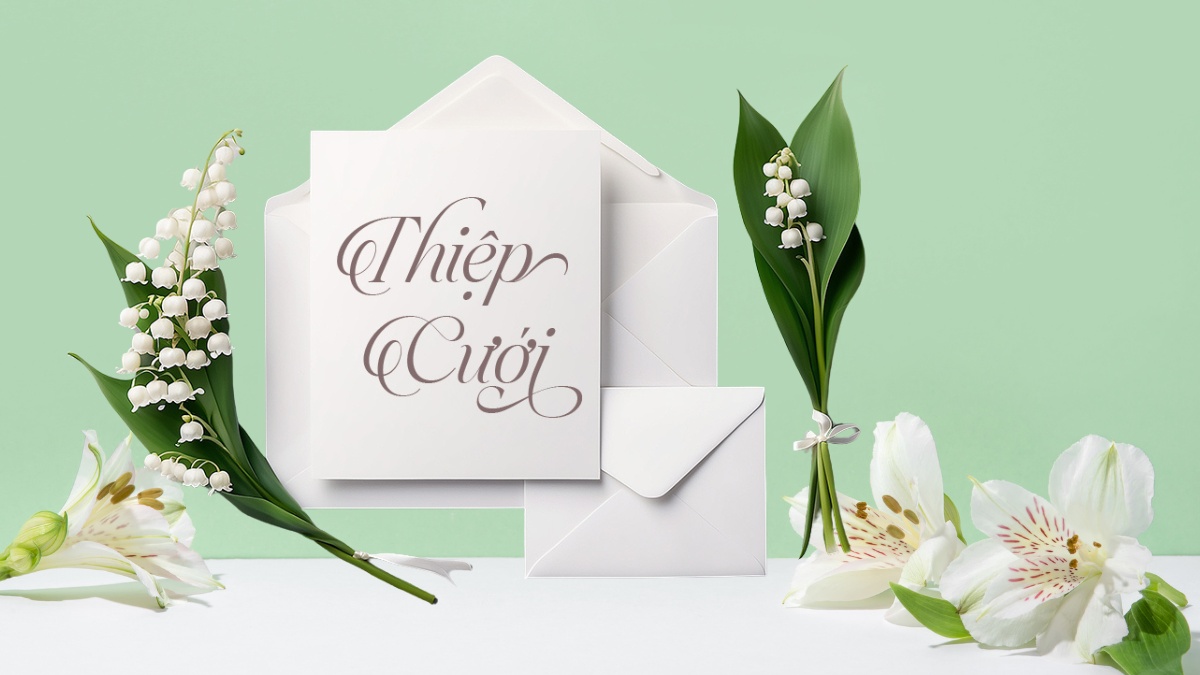
15 Font chữ viết tay tiếng Việt đơn giản, siêu đẹp
Font chữ viết tay tiếng Việt đẹp, đơn giản được ứng dụng rất nhiều trong các sản phẩm in ấn, poster, thiệp mừng... Đây là lựa chọn của nhiều người khi muốn mang đến một thiết kế cổ điển, gần gũi và hiện đại. Nếu bạn muốn tìm hiểu về những font chữ viết tay vintage hay hiện đại, thời thường thì hãy đọc bài viết này. Sforum chia sẻ đến bạn 15 mẫu font chữ đa dụng và phổ biến nhất.
Font VN Griffiths
VN Griffiths là một font chữ viết tay tiếng Việt vô cùng thông dụng và được xuất hiện ở rất nhiều nơi. Đây là sự lựa chọn hoàn hảo để bạn cho ra đời những thiết kế thiệp cưới đầy tinh tế và sang trọng. Với đường nét trang nhã, mẫu chữ này được nhiều người nhận xét rất dễ đọc, không gây rối mắt cũng như tạo cảm giác thanh thoát, nhẹ nhàng. Ưu điểm của font chữ VN Griffiths phải kế đến sự thanh lịch, mềm mại, hơi hướng cổ điển nhưng vẫn rất gần gũi và hài hòa.
VN Lovelista tiếng Việt
VN Lovelista rất được yêu thích bởi font chữ đẹp, đơn giản phù hợp với nhiều dự án thiết kế. Người dùng có thể ứng dụng trong các bài đăng mạng xã hội, trích dẫn, thiết kế logo, bảng hiệu, áp phích, biểu ngữ website,... Điểm nhận dạng của font chữ này phải kể đến những nét thanh đậm rõ ràng mang hơi hướng nhẹ nhàng, bay bổng. Đây chắc chắn là một font chữ hoàn hảo cho các thiết kế đơn giản nhưng vẫn làm nổi bật các thông điệp cần truyền tải.
Font VNI Zap
Nhắc đến những font chữ viết tay đơn giản và mang phong cách hiện đại, gần gũi với người Việt không thể thiếu font VNI Zap. Font chữ này rất phổ biến trong nhiều thiết kế. Đây cũng là lựa chọn hàng đầu của cộng đồng thiết kế đồ họa. Nếu bạn muốn sản phẩm của mình có tính sáng tạo và đột phá thì đừng bỏ qua font VNI Zap. Với sự đa dạng và linh hoạt trong kiểu chữ, các nhà thiết kế sẽ có thêm nhiều cách để truyền tải thông điệp một cách mạnh mẽ, linh hoạt và thu hút.
Font Việt hóa MTD Yessy
MTD Yessy mang đến một lựa chọn đầy tinh tế và quyến rũ, vừa mang phong cách hiện đại lại vừa cổ điển nên có thể đáp ứng nhiều nhu cầu thiết kế khác nhau. Yessy nổi bật với những đường nét vô cùng nhẹ nhàng, tạo sự dễ chịu cho người xem. Phong cách của font chữ viết tay vintage này rất thích hợp trong các ấn phẩm in ấn và trực tuyến. Đây là lựa chọn lý tưởng để tạo ra những sản phẩm mang hơi hướng sang trọng, thanh lịch.
Font MTD Daytonia
MTD Daytonia là font chữ viết tay tiếng Việt được rất nhiều người dùng, gây ấn tượng bởi những đường nét đầy uyển chuyển và mềm mại. Phông chữ này giúp mang lại sự hài hòa, tự nhiên như thể do con người tự viết bằng tay. Daytonia là lựa chọn hoàn hảo cho việc thiết kế các sản phẩm mang tính cá nhân hóa cao như thiệp mời, bao bì, branding… Nó phản ánh xu hướng hiện đại, sang trọng mang hơi hướng tự do, cá tính.
1FTV Eastin Hikary
1FTV Eastin Hikary là một font chữ đẹp, ấn tượng, mang đến một cảm giác nhẹ nhàng và thanh thoát trong từng tác phẩm. Font chữ này được sử dụng vô cùng hoàn hảo cho những dự án vintage nhưng vẫn đảm bảo thể hiện được nét đẹp hiện đại, sang trọng. Những đường nét mượt mà giúp người đọc rất dễ nhìn và nhận biết. Font chữ này rất được ưa chuộng khi thiết kế bìa sách, tiêu đề, poster, logo,...
VN Cathiy Betiey
- Người sáng tạo: Jamalodin
- Phụ trách tiếng Việt: Huy Nam
VN Cathiy Betiey là font chữ vô cùng độc đáo với nét đặc trưng của những đường nét thanh, đậm rất rõ ràng. Đặc biệt, kiểu chữ in nghiêng mang đến sự uyển chuyển, nhẹ nhàng, lả lướt và tinh tế. Với phong cách độc đáo, ấn tượng, font chữ viết tay đơn giản này có thể ứng dụng nhiều trong các ấn phẩm in ấn, thiệp mời, logo,... VN Cathiy Betiey là lựa chọn tuyệt vời để người dùng có thể truyền đạt cảm xúc qua từng con chữ.
1FTV VIP Bengoda tiếng Việt
- Người sáng tạo: Rantautype Studio
- Tiếng Việt: Kiên 2K7 (Trung Kiên)
Font chữ Việt hóa viết tay 1FTV VIP Bengoda là một phông chữ rất thích hợp để sử dụng trong thiết kế có phong cách tối giản, lịch thiệp. Những đường nét không cầu kỳ nhưng vẫn đảm bảo độ mượt mà và nhẹ nhàng. Font chữ viết này được pha trộn giữa phong cách hiện đại, đơn giản vừa mang đến sự ấn tượng, độc đáo vừa mang hơi hướng vintage, cổ điển. Nét chữ in nghiêng nhẹ nhàng, uyển chuyển như đang nhảy nhót trên trang giấy.
Trên đây là 15 mẫu font chữ viết tay đơn giản, đẹp nhất mà Sforum chia sẻ đến bạn. Đây là những kiểu chữ có tính ứng dụng cao trong thiết kế và có thể xuất hiện trong nhiều ấn phẩm như poster, logo, thiệp cưới,... Từ kiểu font chữ viết tay vintage đến các font tiếng Việt hiện đại, sang trọng, tinh tế, chắc chắn sẽ khiến bạn hài lòng để trang trí cho dự án của mình.